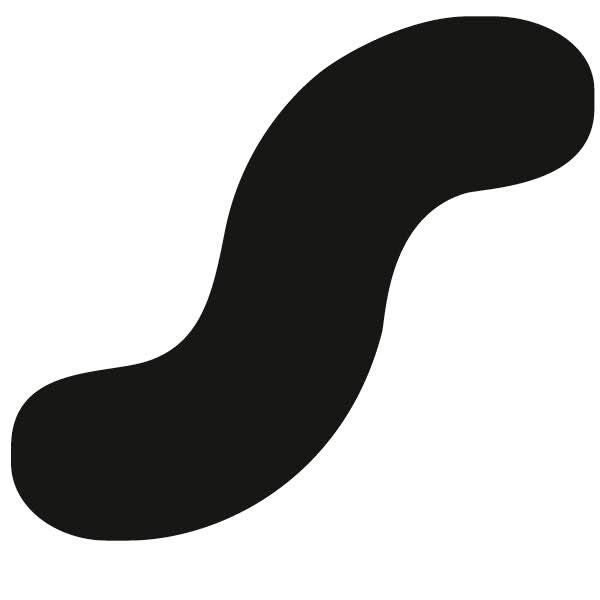
Das lustige Sommerloch-Ratespiel 2009
Mein Produkt brauchst Du, wenn der Fleckenteufel nicht mehr hilft. :tuschel:
Da braucht man doch dann eine Schere, um den Fleck herauszuschneiden, oder? :?
Hihi, das geht auch! Hmmm, vielleicht wird mein Produkt eher von einer weiblichen Zielgruppe verwendet? Glaube ich aber eigentlich nicht … Mensch Jungs, womit übertüncht man denn einen Fleck, wenn man ihn nicht rausschneiden will? (Könnte ja an einer fürs Rausschneiden strategisch ungünstigen Stelle sitzen) ... Stichwort Farbe. Und Textilien. Na?
Noch nie gehört oder gesehen. Scheint wirklich was für Frauen zu sein. :P ;)
weltweit agierendes und bekanntes, deutsches Unternehmen, Hauptsitz natürlich Deutschland.
Firmengeschichte beginnt 1879
später evtl mehr, viel spass :)
Sind denn schon alle in Ferien? Das ist doch Ravensburger!
Ach, so ist das hier? Wenn es zu einfach ist, spielt keiner mit?!
Das will ich sehen!
Au weia, jetzt muss ich mir erstmal was einfallen lassen! Gebt mir eine Mittagspause lang Zeit, dann kommt etwas neues.
muss die ganze Zeit an Brandsalbe denken... :?
(da ist ein ganz unschöner Knick drin, oder hat mein Monitor ne Delle :))
Du meinst die unsaubere Kurve, oder? Stimmt!
Es handelt sich übrigens nicht um Apotheke und nicht um eine Produktmarke, sondern es ist das Logo einer Firma, die Produkte rund um die Gesundheit herstellt. Denkt mal über den schulmedizinischen Horizont hinaus. :tutor: